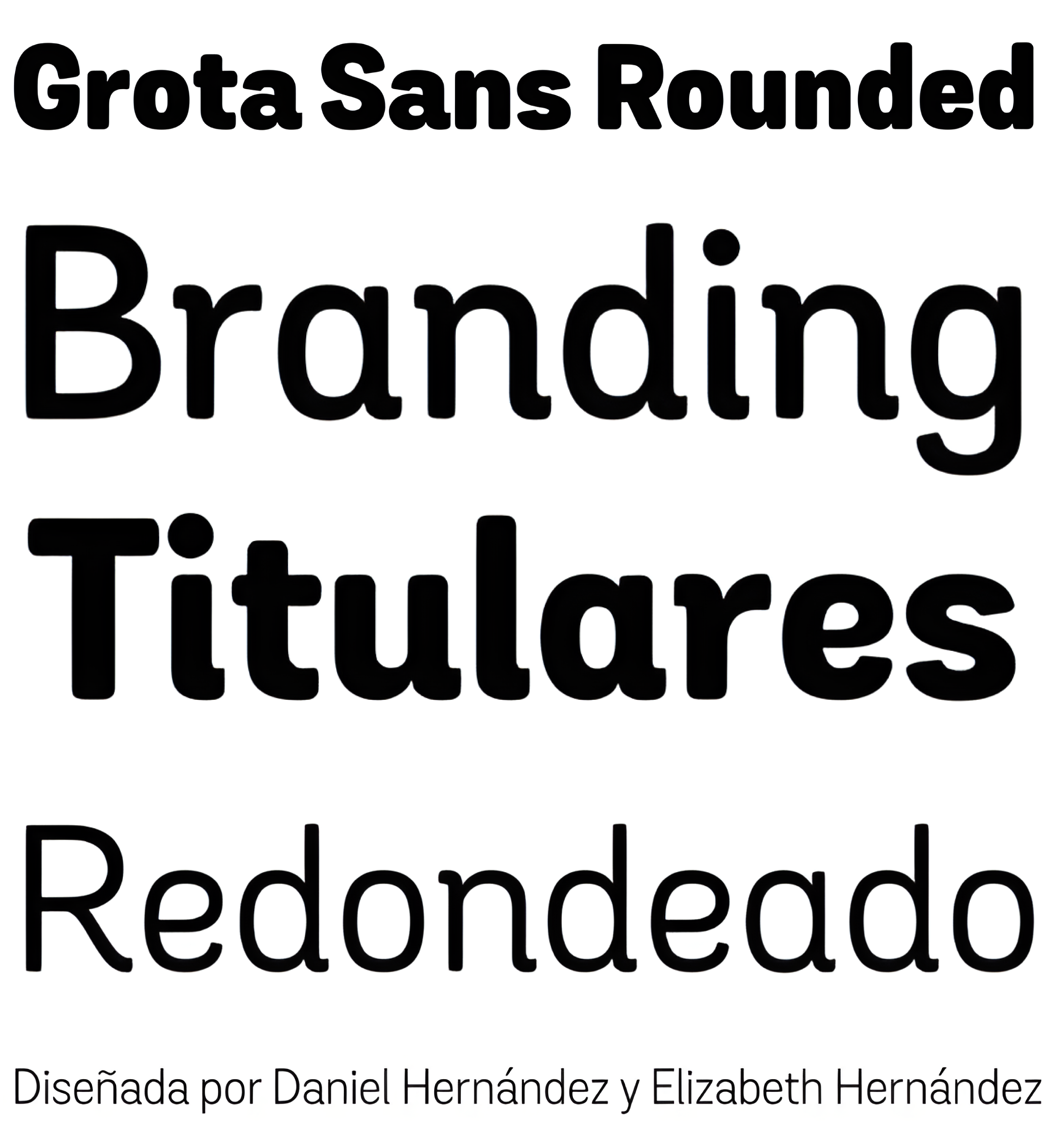
Grota Sans Rounded
| Descripción | Grota vuelve en sus nuevas versiones Sans y Rounded. La familia completa consta de 40 fuentes, 10 pesos diferentes, cursivas y una versión alt. Grota Sans Rounded, diseñada por Eli Hernández y Daniel Hernández, es una fuente grotesca con espíritu latino. Este tipo acompaña a Grota Sans y Grota Unicase. Es ideal para logotipos, marcas, libros, titulares, etc. |